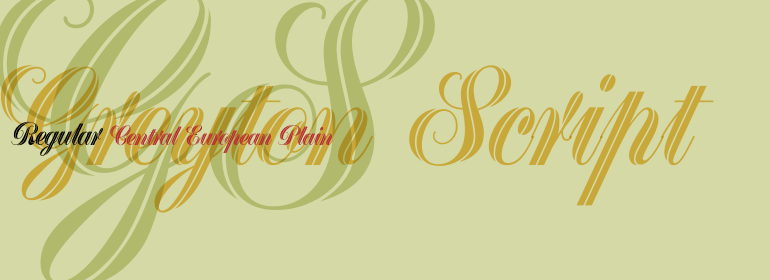
Greyton Script™
Greyton Script™,这款字体结构工整、笔画清晰,兼顾美观与易读性,适用于标题、正文、海报、包装、LOGO 等多种场景。字形优雅稳定,风格百搭耐看,适配日常排版与创意设计,让文字呈现更舒适、更具质感。Greyton Script™一笔一画,皆是细节,以均衡的比例、流畅的线条打造舒适视觉体验,字形端正大气,风格简约现代。无论是商业设计、品牌宣传还是日常排版,都能轻松驾驭,让文字更有格调与力量。Greyton Script™字体下载。
Greyton Script is the work of South African designer Gerhard Schwekendiek, who is known for his script lettering and logos. This copperplate script face looks almost ribbon-like, a feeling accentuated by the letters' fine inline. Greyton Script is perfect for eye-catching headlines or personal invitations and greetings.